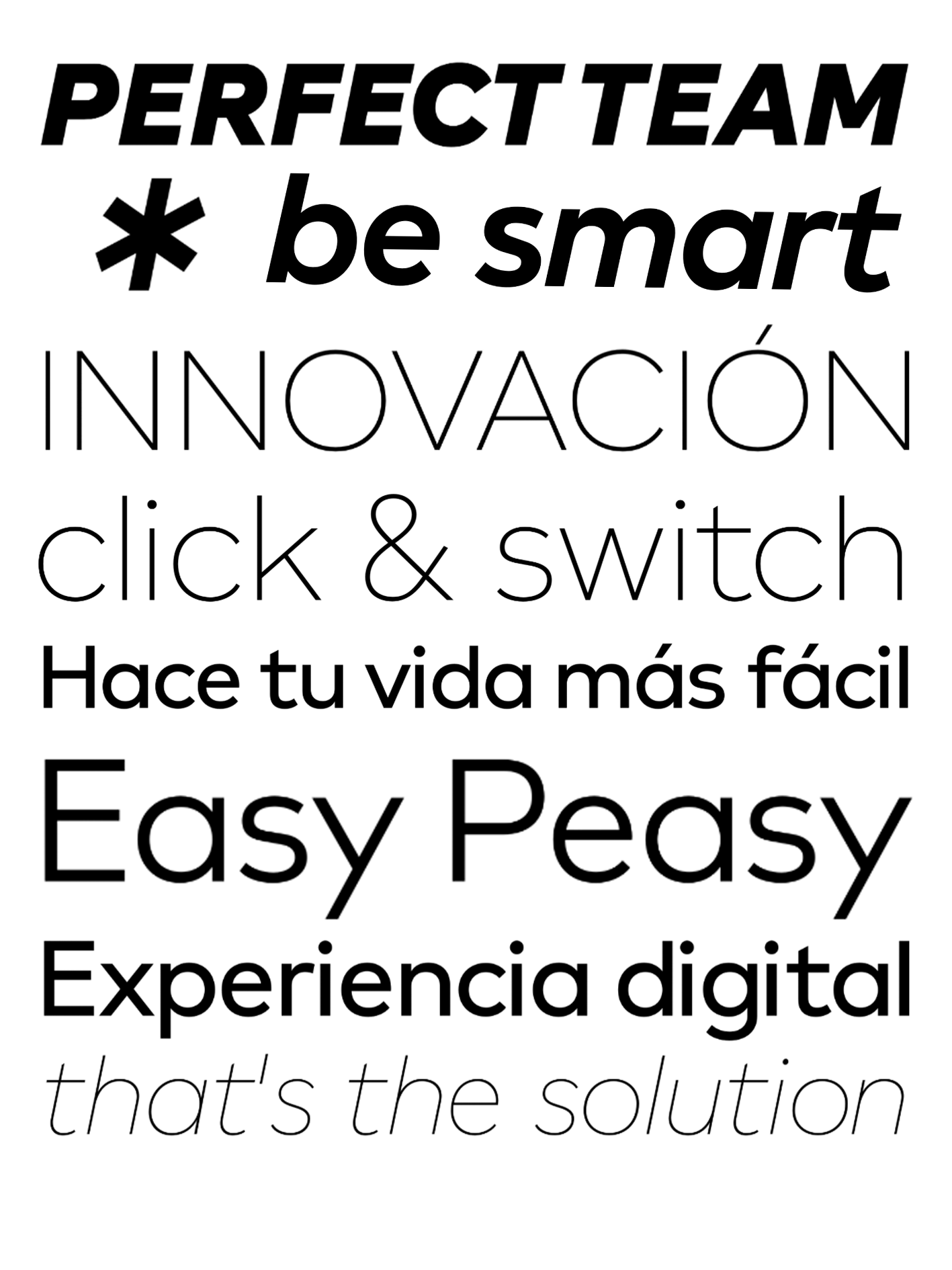
| Descripción | Diseñada para ser nítida, precisa para el crecimiento. Glyphic Sans es una sin gracias que vive en la intersección entre lo técnico y lo humano. Construido sobre proporciones geométricas, este tipo de letra incorpora sutiles inflexiones humanistas que le confieren personalidad sin sacrificar la claridad, especialmente visibles en los trazos extendidos y las elegantes diagonales de K, Q, y, k y otros caracteres distintivos. Con ocho pesos -incluido un negro especialmente atrevido-, detalles refinados y una estructura equilibrada, es la elección natural para empresas de tecnología financiera, marcas bancarias y compañías tecnológicas que buscan proyectar confianza, innovación y sofisticación. Desde logotipos hasta interfaces digitales, Glyphic Sans transmite profesionalidad con un toque distintivo. Concebida originalmente para marcas denominativas cortas -donde sus detalles brillan con mayor intensidad-, esta fuente resulta igualmente versátil en textos más largos, manteniendo la legibilidad y el ritmo visual en aplicaciones editoriales, presentaciones corporativas y campañas digitales. No es fría, pero tampoco efusiva. Glyphic Sans tiene autoridad sin distancia y elegancia sin afectación. |